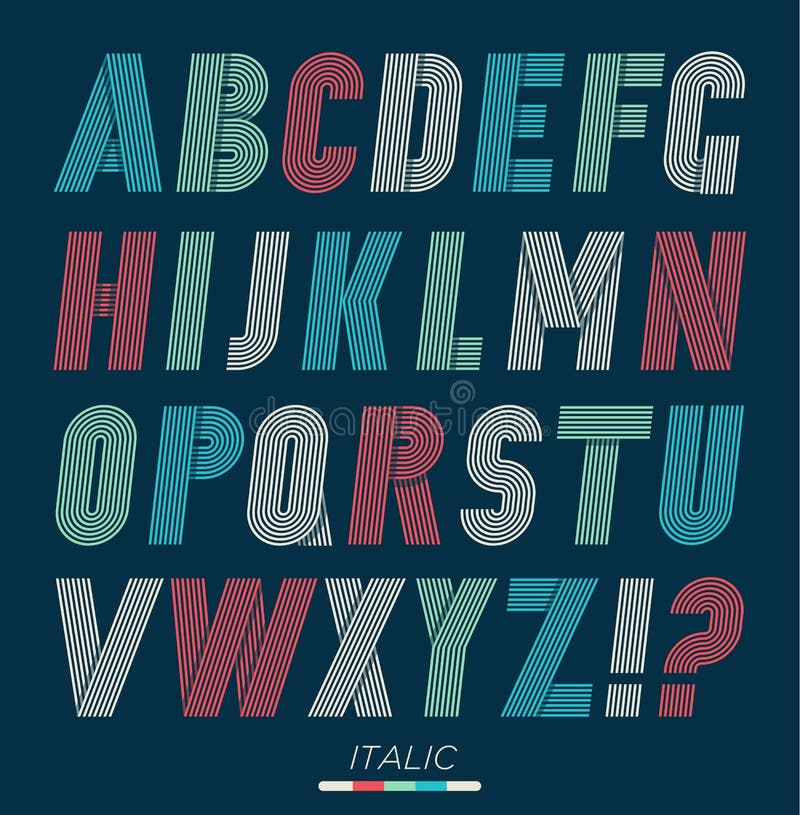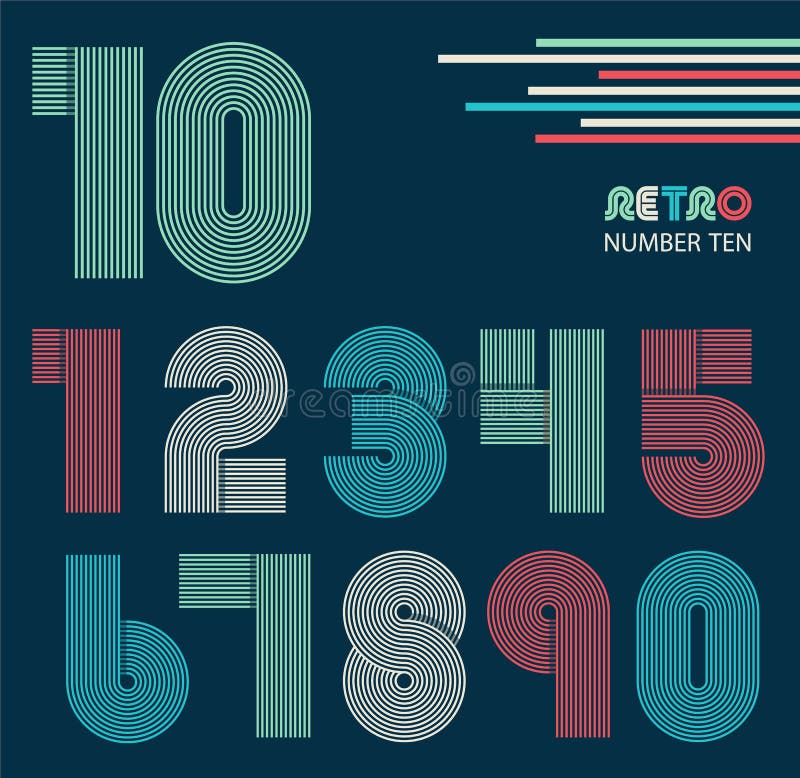
Установленные шрифты ретро нашивок в стиле фанк. Установленные шрифты, ультрамодный элегантный ретро дизайн ретро нашивок в стиле фанк стиля вектор техника eps конструкции 10 предпосылок